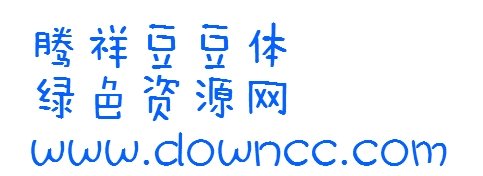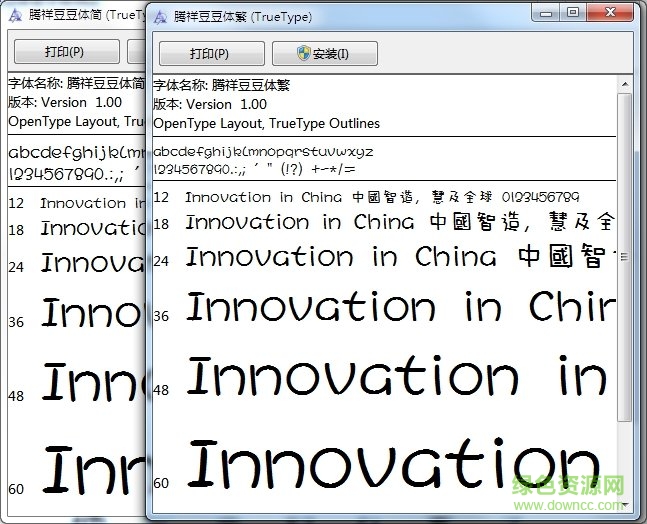
騰祥豆豆體字體打包包括騰祥豆豆體簡(jiǎn)體和繁體,讓用戶可以盡情體驗(yàn)本字體帶來(lái)的設(shè)計(jì)樂(lè)趣,字跡充滿兒童特色,圓潤(rùn)可愛(ài)的造型,更加吸引孩子們的眼光,綠色資源網(wǎng)歡迎大家免費(fèi)下載使用!
騰祥豆豆體為美術(shù)字體,風(fēng)格鮮明、特點(diǎn)突出。豆豆體書(shū)寫(xiě)模仿幼兒書(shū)寫(xiě)方式,筆畫(huà)隨意放松,富于變化,凸顯稚嫩無(wú)暇,天真童趣的特點(diǎn)。本款字在不影響閱讀的前提下盡顯其特性,且該字體可免費(fèi)下載并用于非商業(yè)用途。
騰祥豆豆體字體模仿幼兒的書(shū)寫(xiě)方式設(shè)計(jì),比較兒童化,天真童趣,很適合用來(lái)出版兒童讀物、包裝設(shè)計(jì)、廣告設(shè)計(jì)、網(wǎng)頁(yè)設(shè)計(jì)等。